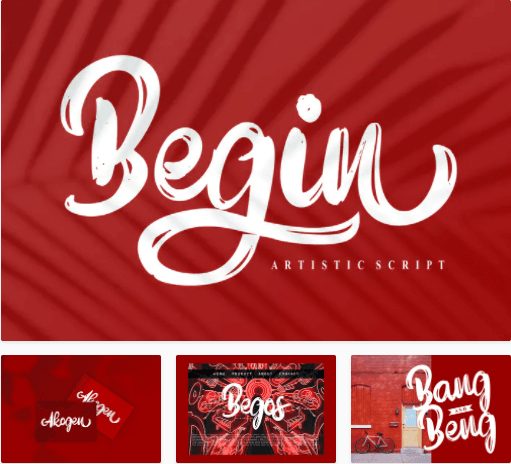
Begin Font
Begin Artistic Script - это новый подлинный шрифт, подходящий для многих ваших визуальных потребностей, таких как приглашения, поздравительные открытки, материалы для брендинга, визитные карточки, цитаты, плакаты и многое другое!
Этот шрифт открытого типа имеет такие функции, как стилистические наборы, стилистические альтернативы, контекстные альтернативы, SWASH и лигатуры. Доступ к функциям Open Type можно получить с помощью открытых программ, таких как Adobe Illustrator, Adobe InDesign, Adobe Photoshop Corel Draw X версии и Microsoft Word. И этот шрифт дал юникод PUA (специально закодированный шрифт). так что все альтернативные символы могут быть легко доступны в полном объеме